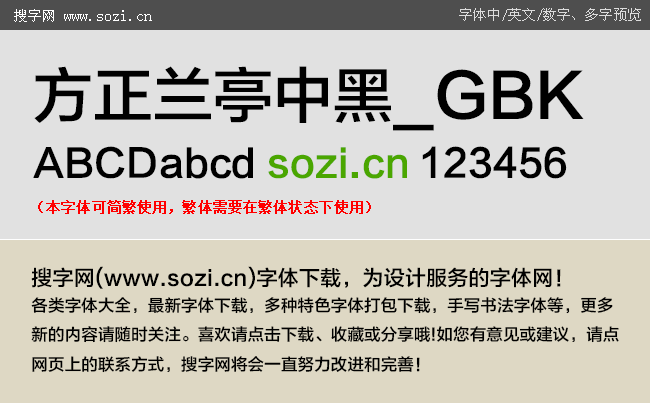
方正蘭亭中黑-GBK
搜字網(wǎng)提供一款方正蘭亭中黑-GBK下載,方正蘭亭中黑是一款比一般系統(tǒng)黑體粗的字體,該字體結(jié)構(gòu)優(yōu)美,識(shí)別性強(qiáng),端正大方,筆鋒粗曠,整體風(fēng)格出色,且GBK編碼包含文字更全,適用于廣告設(shè)計(jì)、名片設(shè)計(jì)、包裝印刷、產(chǎn)品設(shè)計(jì)等應(yīng)用。